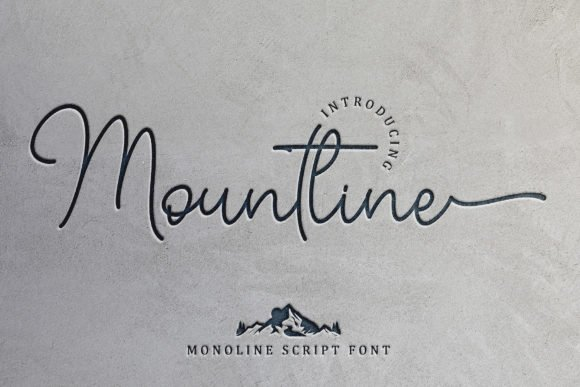
Название: Mountline Font (2021)
Mountline - это нежный и элегантный рукописный шрифт.
Его отчетливые и хорошо сбалансированные буквы делают этот шрифт шедевром.